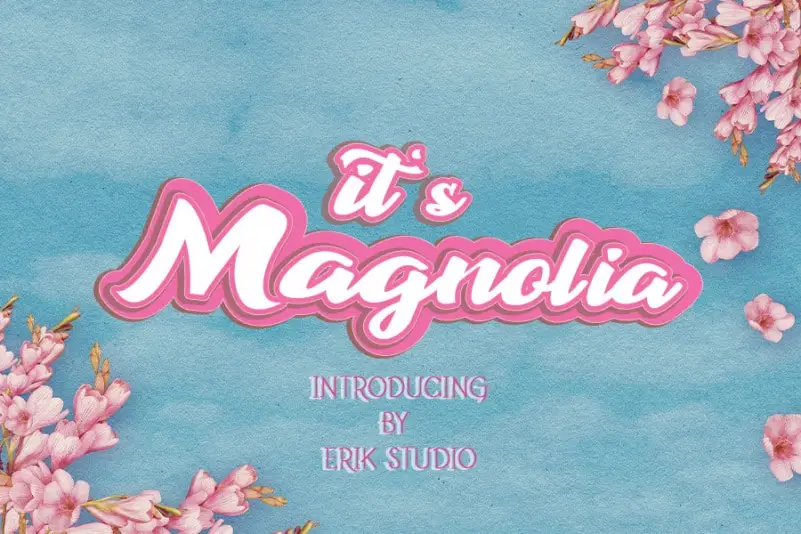
It’s Magnolia Bold Script Font – Download Grátis
A It’s Magnolia Bold Script Font é uma elegante fonte para display que transmite uma sensação acolhedora e simpática. Seu estilo cônico torna-a perfeita para um vasto leque de projetos, estendendo-se naturalmente para aplicativos como cartazes, títulos de mídia social, ou até mesmo logotipos de marcas jovens. Com o seu design divertido e elegante, você tem a liberdade para imaginar tantas maneiras criativas quanto suas ideias possam surgir. Engane-se: não há limites à sua imaginação quando escolhe esta fonte. Seja a próxima peça de um design poderoso ou única, It’s Magnolia é perfeita para qualquer projeto em que você queira destacar seu toque personalizado.